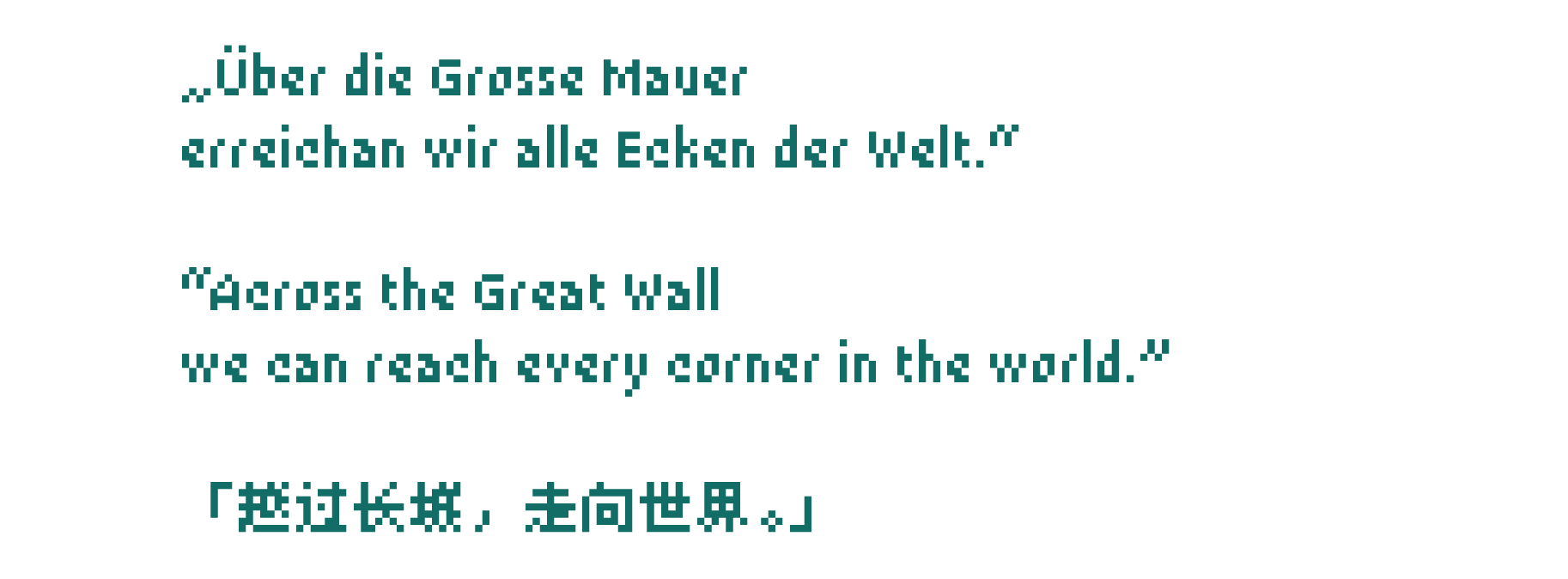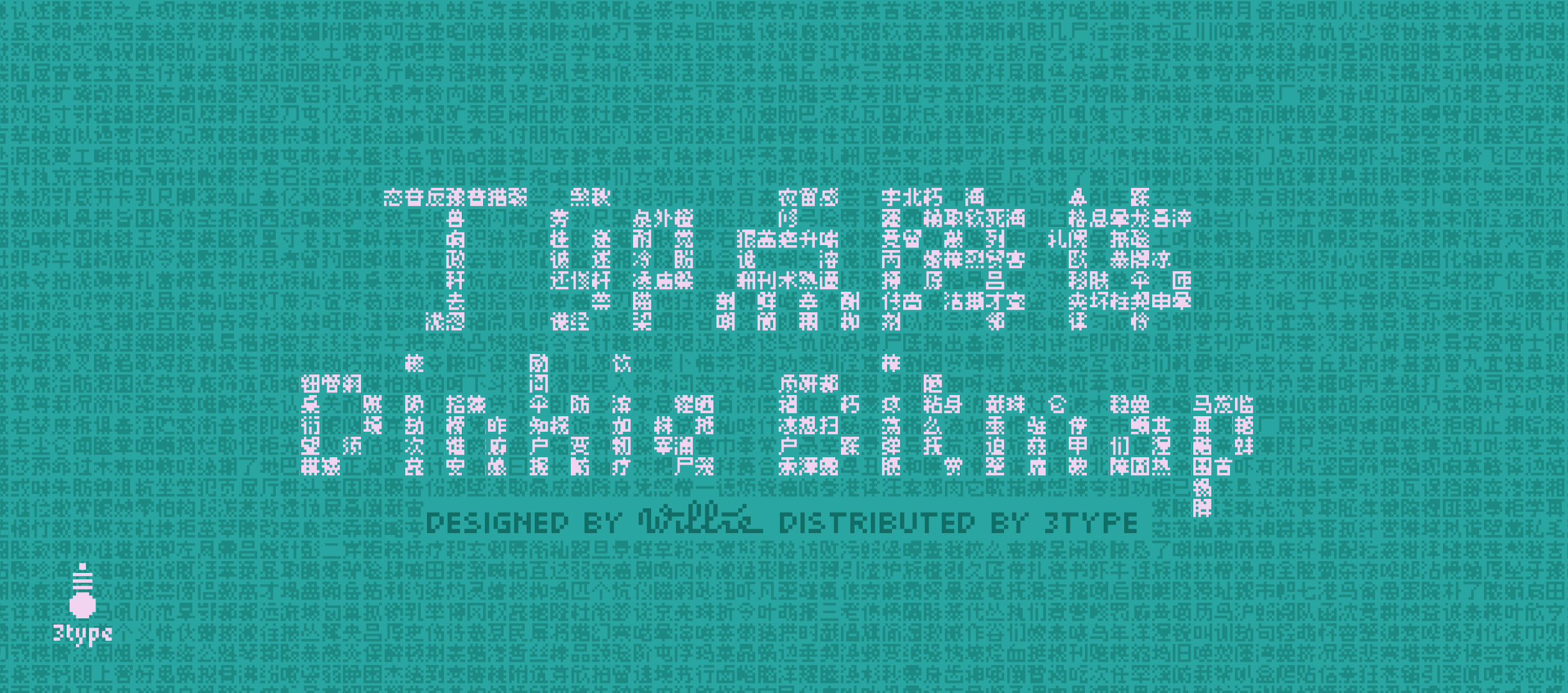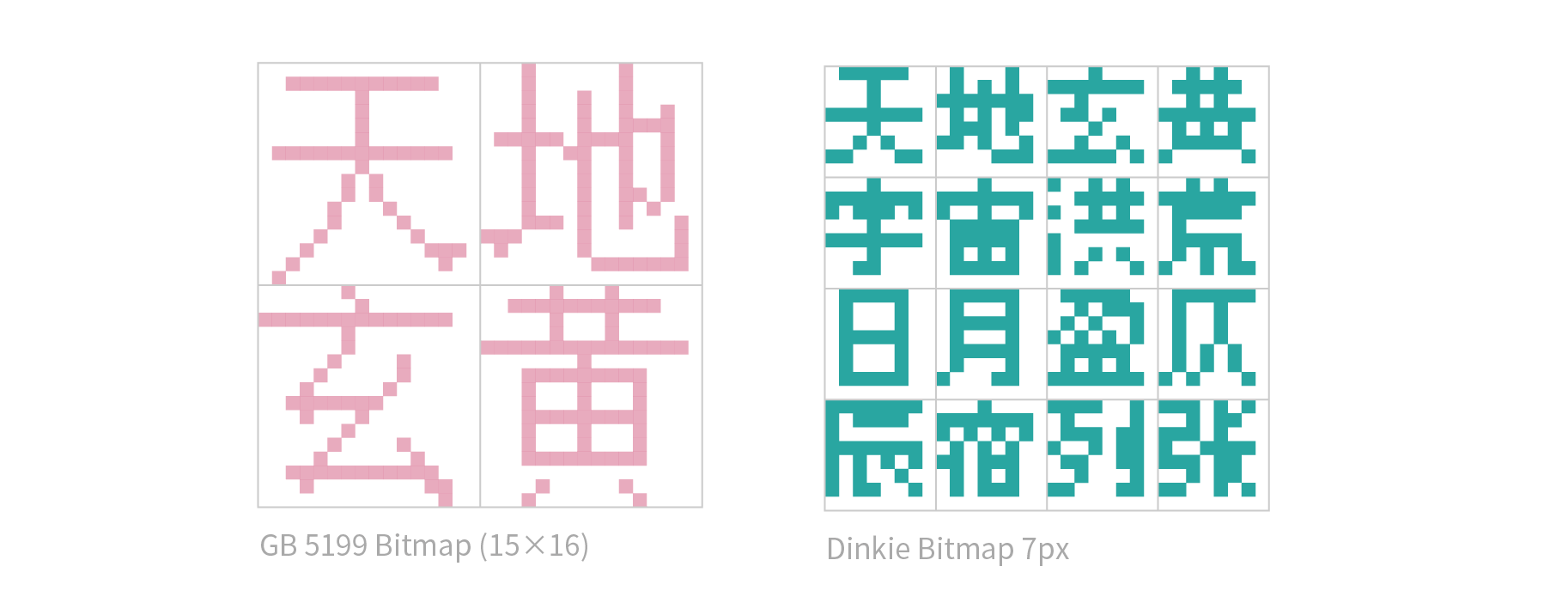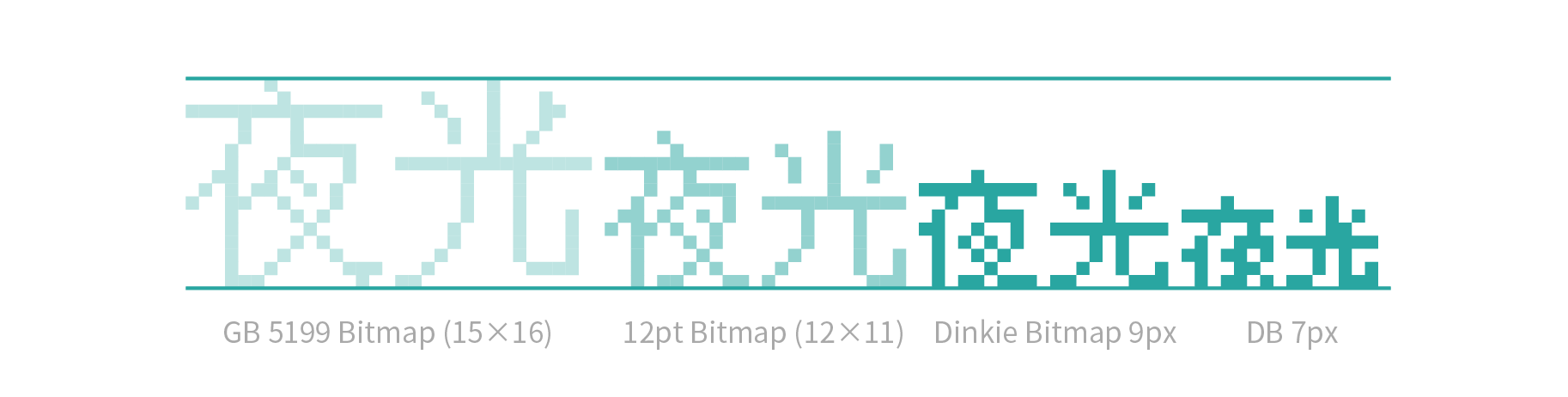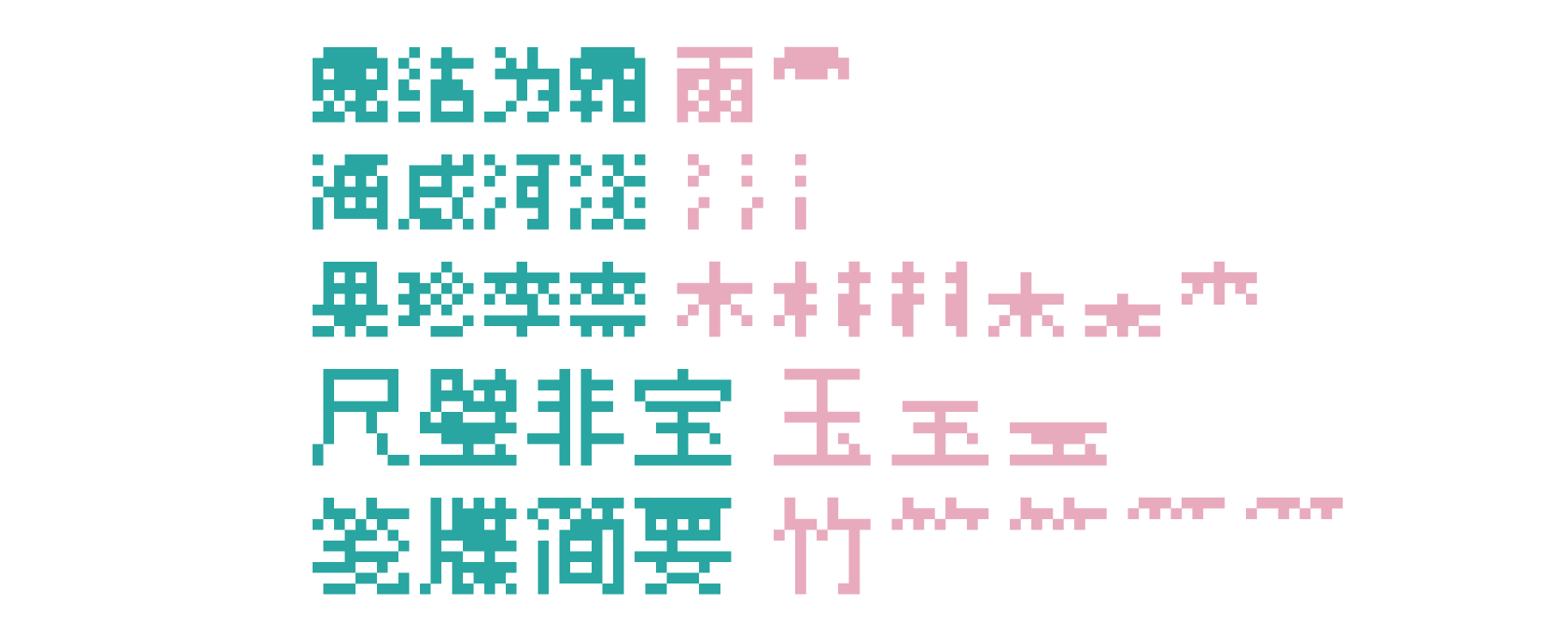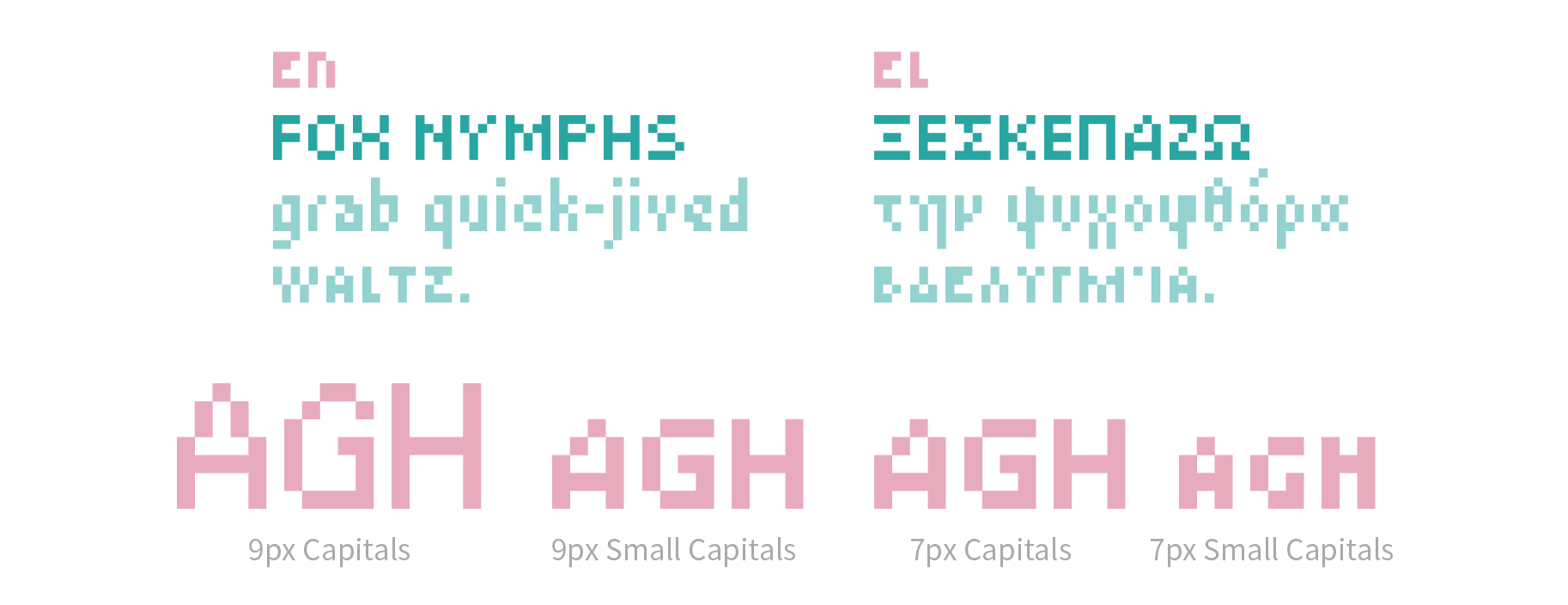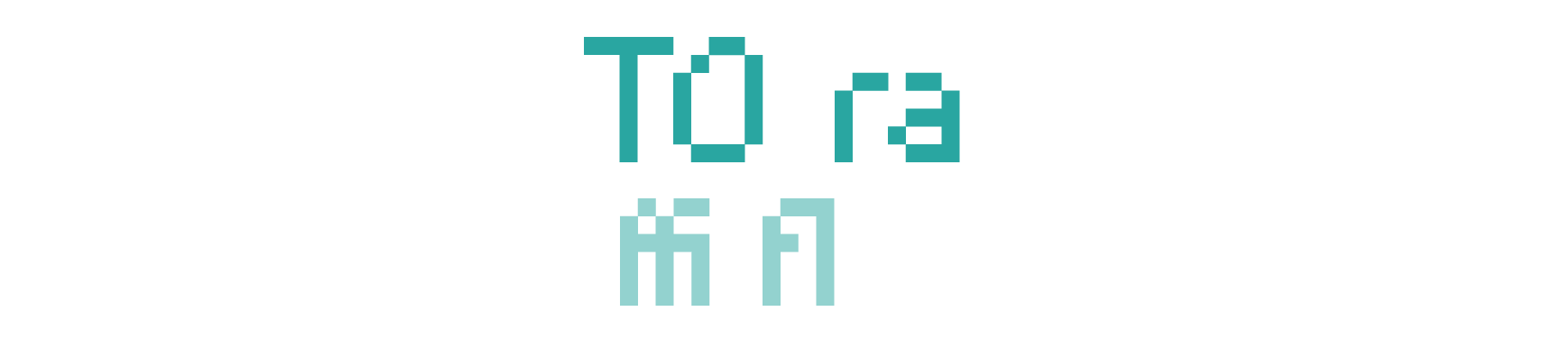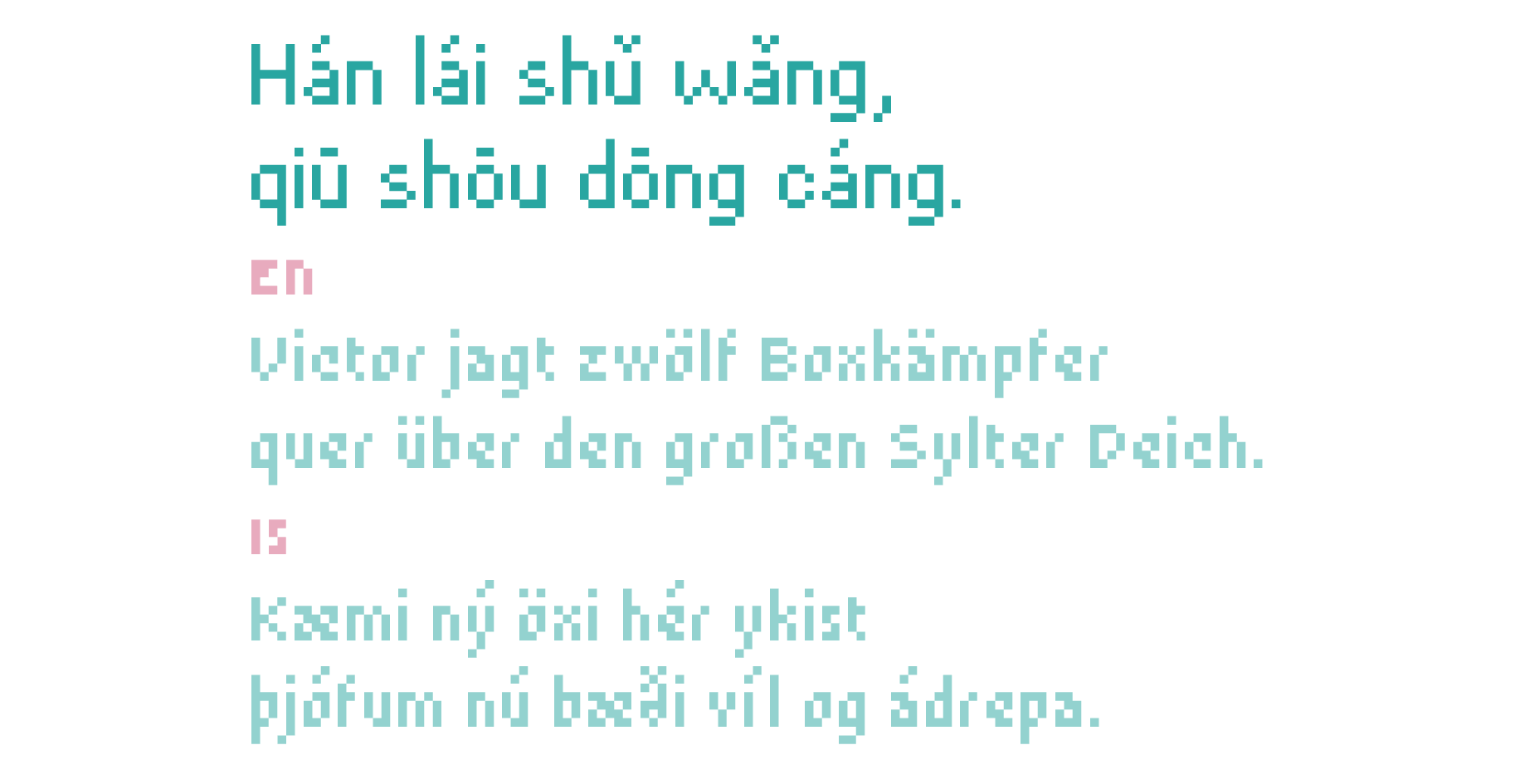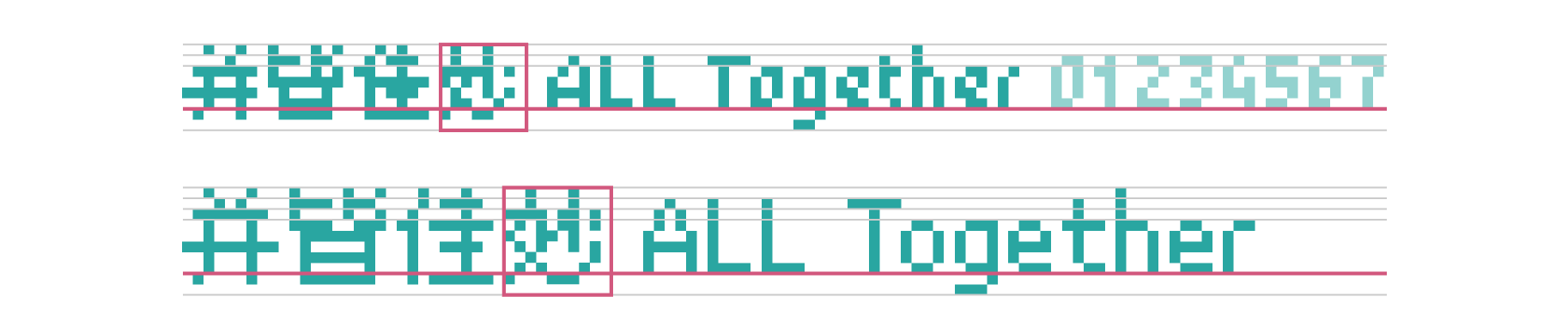
1987 年 9 月 20 日,一封电子邮件从北京发至德国卡尔斯鲁大学。邮件由英德双语写成,开头一句话便是「越过长城,走向世界」。
——这是中国向海外发出了第一封电子邮件,中国的互联网时代随之到来。这一年,正是农历丁卯年。
如今,计算机和互联网早已融入我们生活的方方面面,而这一切的背后,是一代科学家和工程师的付出。「丁卯点阵体」以此命名,意在致敬那些将中文世界带入信息化时代的先驱们。
「丁卯点阵体」是一套像素风格的中文字库,设计初衷是探索小尺寸像素汉字的可能性。经过实验,确认汉字在最低 7×7 的像素网格中仍然可读——这一尺寸,是最常见的国标点阵字(16×16)的四分之一。
之后,经过长达三年的设计开发,为之匹配了外文字母和标点符号,又全新匹配了一套 9×9 的像素字体。今年上半年面向公众开放了试用版本后,收到了热烈的反响;经过上个月的预售活动后,全套字体终于在今天正式发布了!
这是迄今为止第一款小至 7×7 的中文像素字体,也是唯一一款 9×9 的矢量格式的像素字体。为像素画创作、游戏开发、风格化平面设计开启了全新的可能性。
设计
「丁卯点阵体」分为 7px 和 9px 两个尺寸,全部汉字都在 7×7 和 9×9 的像素面积中表现。在这样有限的空间中,笔画的减省和粘连无可避免——但设计师尽量还原汉字的整体造型特征,让每个字都具有相当的可识别性,在上下文语境中则可以流畅地读出来。
在设计的过程当中,总体上并不回避笔画堆积造成的黑色「斑块」。尤其对于笔画多的字而言,有时「笔画密集」正是这个字的主要特征。
相对于 7px,9px 的设计空间要宽裕得多,因此有机会让笔画之间的区分更加明显,大段文字的阅读也更轻松。两者配套使用,可以在极低分辨率的环境下形成信息层级。
虽然可用的像素尺寸很小,但依然提供了一定的发挥空间,因此这套字体中,设计师根据不同字的需要,调节偏旁部首的宽度和细节,并在整体上保持风格一致。
「丁卯点阵体」中匹配设计了整套西文部分,包括拉丁字母、希腊字母、西里尔字母。这里并不只是功能性的随意匹配,而是和汉字部分同样的「小尺寸极限」的追求。
其中 7px 的大写字母是可保持清晰的最小拉丁字母尺寸——大写 5px 高;小写字母则在极限的 4 像素 x 高度(字母 n、x、 v 等所占的纵向空间)中完成。在此基础上,甚至制作了仅 4 像素高的小型大写字母!
每对字母之间的字偶间距都经过精心的调整(以像素为单位),让它们间距适中;另外也设计了可以自由开启的自动合字功能。
「丁卯点阵体」中的拉丁字母不仅 26 对大小写字母,还包括带有各种变音符号的扩展拉丁字母。这套字体不仅可以用于英语,还可以用于德语、法语、意大利语、冰岛语……以及汉语拼音。
拉丁字母的大小是根据汉字大小精心推敲而来的。这样的设计可以让汉字无论和大写字母还是小写字母混排时,都能获得最和谐的效果。
另外,还专为网页排版设计了 9px 基础拉丁字母部分的意大利斜体和等宽两个版本。意大利斜体的设计也相当有趣且极端,大家不妨自己试用体会一下!
还配备了颇有「东亚特色」的全宽字母和半宽假名。这两种字符都是早期像素游戏中的熟面孔,如今制作复古游戏的时候也少不了它们。
高级排版功能
「丁卯点阵体」虽然看上去是像素的,但并不是老旧的像素字体格式,所有的「像素」都是由轮廓围合出来的。
作为一款当代的字体,「丁卯点阵体」配备了丰富的高级排版武器——这是坊间称做「OpenType 特性」的字体功能。在专业的平面设计和排版软件(比如 Adobe InDesign 和 Illustrator)以及网页开发中,它能够让文字以更加灵活的方式呈现。
比如,按照西方排版惯例,自动将一些字母连写的「合字(ligature)」功能:
(你也可以选择关掉这样的连写。)
比如,使用更古典的、可以伪装成小写字母的「老式数字(old-style figures)」:
再比如这个小细节:Q 的尾巴可以自动给后面的字母让出位置——
以及竖排汉字的标点符号会移动到字框的右上角,这也是 OpenType 特性所实现的。
字体技术指标
7px 包含 GB/T 2312–80 字符集及其他常用字(共 7300+ 汉字,遵循大陆字形标准)、拉丁字母、扩展拉丁字母、西里尔字母、希腊字母、日文假名和其他杂项符号。
9px 包含 GB/T 2312–80 字符集及其他常用字(共 11000+ 汉字,覆盖两岸三地及日文常用汉字,遵循大陆字形标准)、拉丁字母、扩展拉丁字母、西里尔字母、希腊字母、日文假名和其他杂项符号。
9px Italic 和 9px Code 包含 ASCII 字符集(基本拉丁字母及数字和标点符号)。
应用展示
「丁卯点阵体」丰富的字符集大大扩宽了它的应用范围。其中配备的各类图标字符可以显著丰富其应用效果。
如今像素复古之风盛行,除了常居一隅的像素风独立游戏和插画,早期的计算机界面、红白机和街机游戏、单色屏功能机以及 QQ 秀等古早产物也常常被人提起。而这些,就是「丁卯点阵体」的原生应用场景。
如果可以应用在公交、地铁的 LED 显示屏上,更是能大大提高信息密度——
由于「丁卯点阵体」字形大幅简化、文件体积小,适合用作 Webfont(网页字体),这在中文字体中是极其难得的。
作为一款现代的 OpenType 轮廓字体,「丁卯点阵体」的使用场景也不局限于低分辨率的场景。应用于平面设计、户外广告等场合,也能传达出一种复古感或科技感。